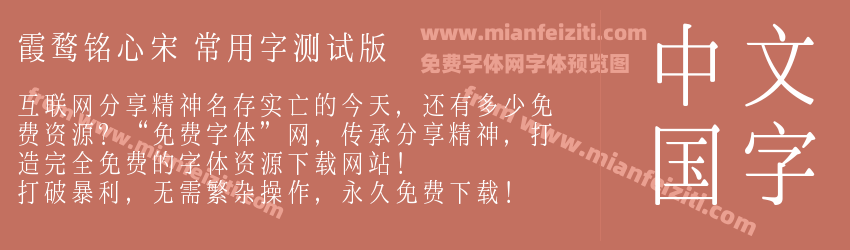
字体风格: 宋体
霞鹜铭心宋在こころ明朝体的基础上修改制作,将新致宋字面横向压缩 85%,并增加圆角,更加清瘦、圆润。(注:铭心宋所收字符相比于新致宋会有所欠缺,敬请留意。)
霞鹜铭心宋目前包含 GB/T 2312-1980 一级字、《通用规范汉字表》一级字、《现代汉语常用字表》3500 字。
本款“霞鹜铭心宋 常用字测试版”是一款书写很新颖的字体,字体大方,适合各种设计作品使用!欢迎下载!